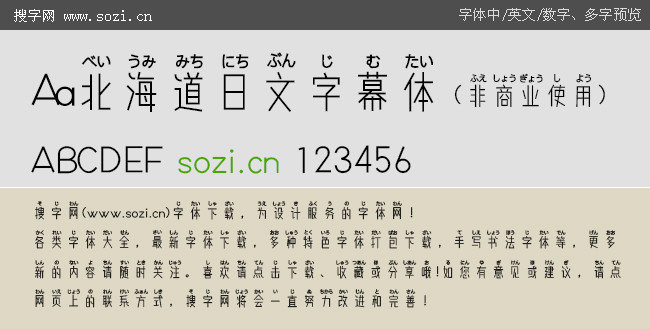
Aa北海道日文字幕體
搜字網(wǎng)給大家提供一款A(yù)a北海道日文字幕體(非商業(yè)使用)字體下載,該字體是一款帶有日文標(biāo)注的中文字體,中文字體簡潔大方,每個(gè)字上面標(biāo)注有日文。適合書裝設(shè)計(jì)、包裝設(shè)計(jì)、海報(bào)設(shè)計(jì)等應(yīng)用(此字體為個(gè)人非商用版,商用可以聯(lián)系QQ:1006760504)。